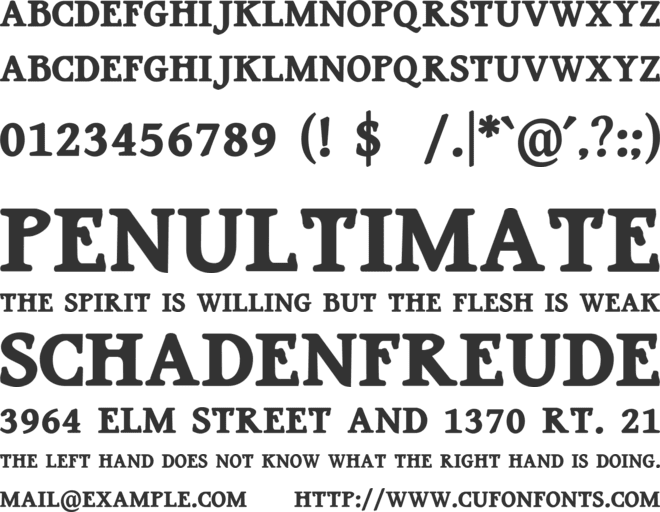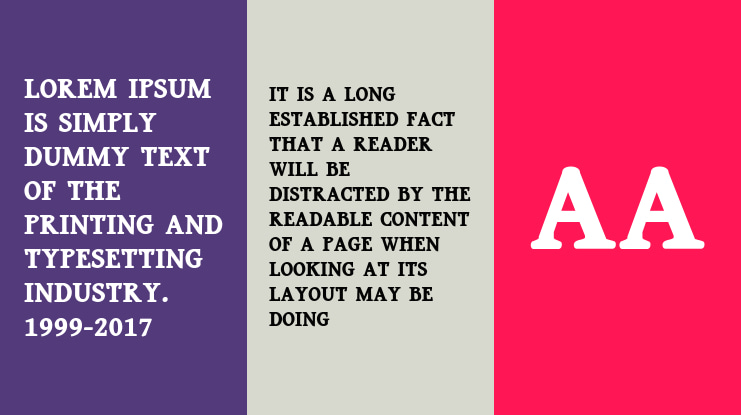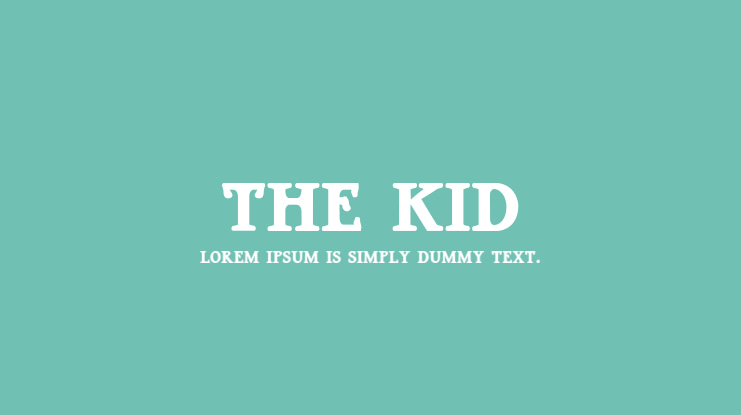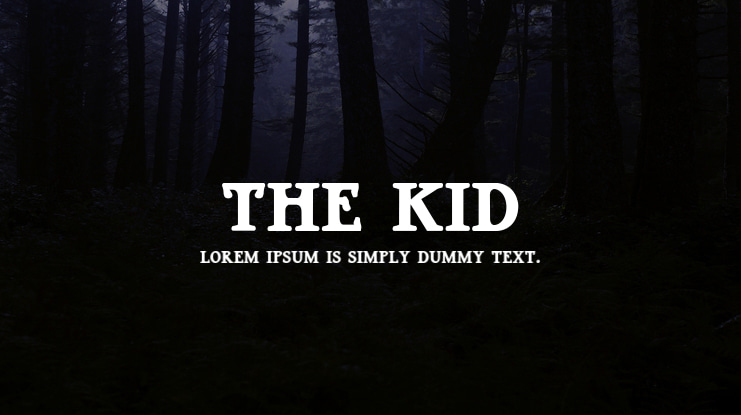
The Kid Font
P. A. Vannucci
Direttamente dal film diretto e interpretato da Charles Chaplin, il font inedito per tutti gli estimatori del film.
Directly from the film directed and starring Charles Chaplin, the unpublished font for all admirers of the film.